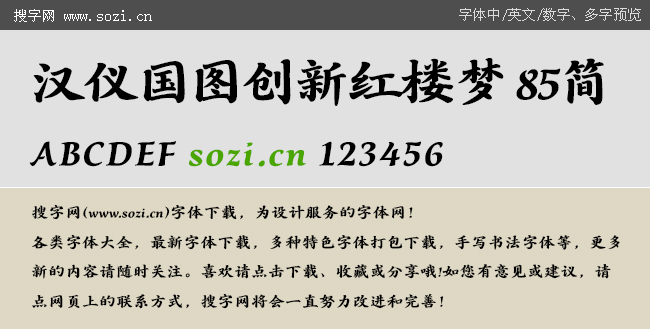
漢儀國(guó)圖創(chuàng)新紅樓夢(mèng) 85簡(jiǎn)
搜字網(wǎng)給大家提供一款漢儀國(guó)圖創(chuàng)新紅樓夢(mèng) 85簡(jiǎn)中文字體下載,漢儀國(guó)圖創(chuàng)新紅樓夢(mèng)字體家族是一套藝術(shù)楷體字體,字體共擁有五款字重,字體簡(jiǎn)潔大方,整體效果非常不錯(cuò)。適用于畫(huà)冊(cè)設(shè)計(jì)、海報(bào)設(shè)計(jì)、包裝設(shè)計(jì)等場(chǎng)合使用。(本字體為個(gè)人非商用版,如需要商用請(qǐng)聯(lián)系漢儀公司購(gòu)買(mǎi)版權(quán))